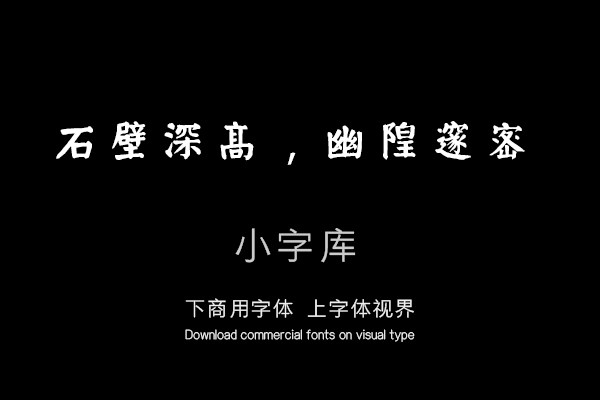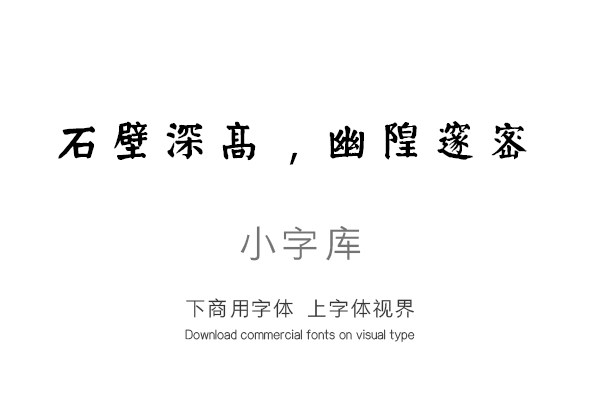
汉标钱沣颜楷水经注
《汉标钱沣颜楷水经注》是一款根据清代钱沣颜楷《水经注》,经过再次调整制作的小字库,该小字库共收录了该真迹作品中约88个字体。
石壁深高,幽隍邃密,林障秀阻,人跡罕交。东南隅有石室,盖太公所居也。水流次平石钓处,即太公垂钓之所也。其投竿跽饵,两膝遗跡犹存,是有磻溪之名也。其水清冷神异。忠叙吾兄雅鉴,沣。